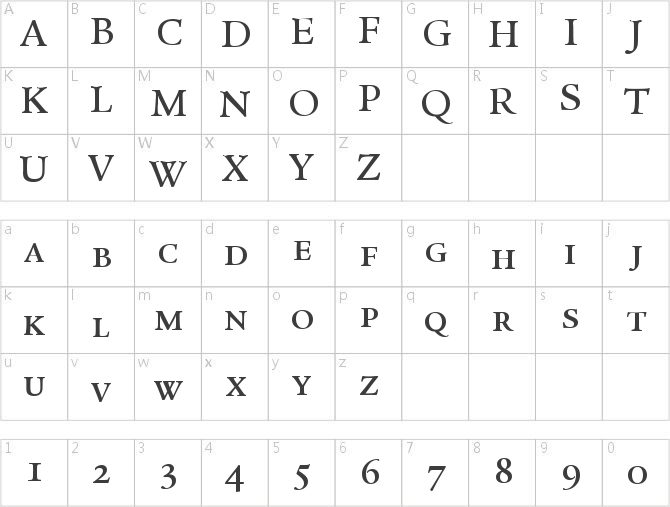
Legacy-Serif-Md-SC-ITC-TT-Med 詳情頁
字體名稱: Legacy-
Legacy-Serif-Md-SC-ITC-TT-Med
Legacy-Serif-Md-SC-ITC-TT-Med介紹
Legacy-Serif-Md-SC-ITC-TT-Med字體字庫是一款讓人賞心悅目、百看不厭的英文字體,適合各類廣告和產品包裝設計應用,字體大小0.08MB,格式為ttf字體,上傳用戶是青檸檬,作者/版權方為未知